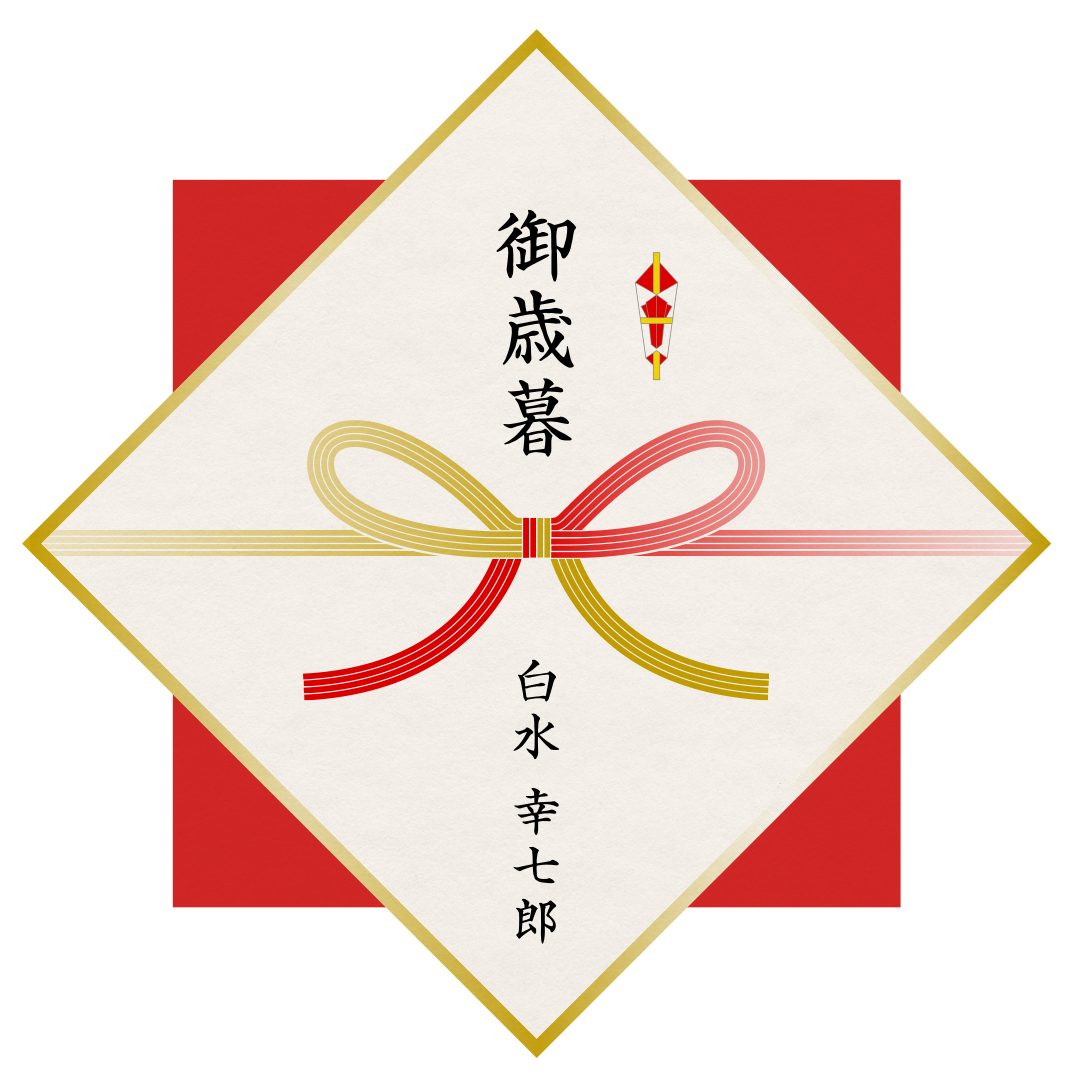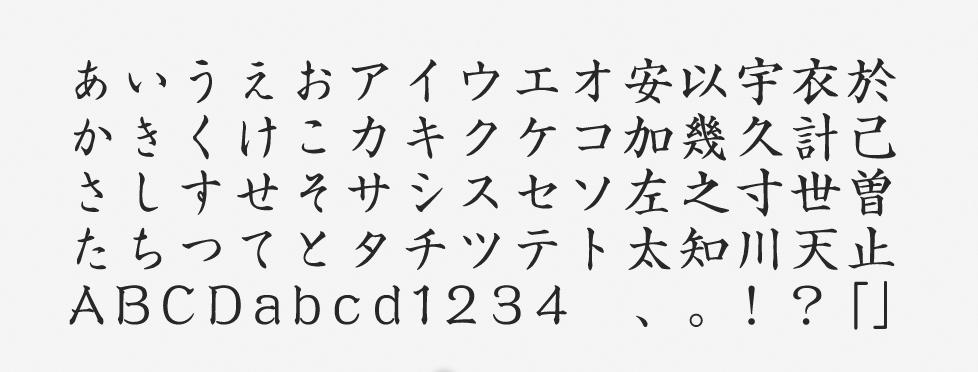
「正楷書CB1」について
正楷書CB1は、正統派の楷書体として開発されました。正確な筆法と力強い書風が特徴で、オーソドックスな楷書体です。楷書は4世紀頃に隷書が変化して誕生し、5~7世紀の唐の時代に完成し、洗練されました。印刷書体となってからも重要な文書に長く使われ続けています。正楷書CB1はその楷書体の1つの完成形とも言えるフォントです。
「正楷書CB1」の特徴
正確な筆法と力強い書風で、格調高いフォントです。オーソドックスであるため使いやすく、礼節を重んじる場面でも安心して使用できます。線が太すぎないため、デザインを上品に仕上げる狙いがある場合にも最適です。
縦画は筆の入り方や太さで安定感があり、横画は凛々しくシャープな印象の右上がりのデザインに仕上げられています。ハネや止めなどもしっかりと丁寧に設計されており、正統派の筆書ならではの美意識を忠実に表現したフォントです。
今回の作例のような制作物では、奇をてらう必要はありません。熨斗紙の宛名書きは手書きの文化が長くあり、今も手書きの対応をしているところが多いでしょう。そのような背景を考慮すると、正楷書CB1のような正統派の楷書体を採用するのは自然なことです。特に氏名の表記の部分は、楷書体での表記を推奨します。